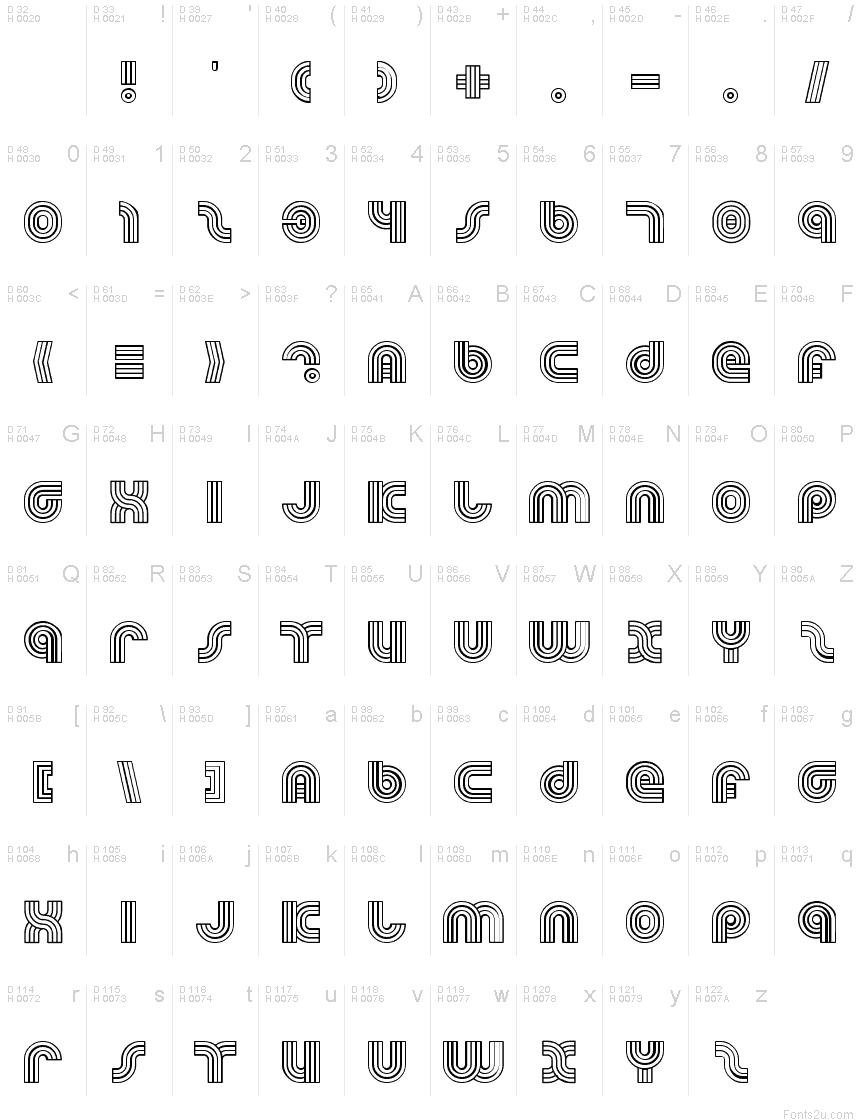
Dreamland von dustBUST Fonts ist eine kostenlose, flippige Display-Schrift, die an handgezeichnete Neonröhren erinnert. Jeder Buchstabe setzt sich aus konzentrischen Streifen zusammen, die sich zu hohen, geschwungenen Formen aufbauen – ein fast hypnotischer, labyrinthartiger Rhythmus. Da die Linien klar und gleichmäßig angeordnet sind, wirkt das Schriftbild trotz der lebendigen Dynamik kontrolliert und gut lesbar.
Setzen Sie Dreamland in großen, fetten Graden ein, damit die geschichteten Bögen auf Musikplakaten, Festival-Branding, Retro-Verpackungen, ausgefallenen Logos, Headlines und Social-Media-Grafiken ihre volle Wirkung entfalten. Diese kostenlose Schrift glänzt vor allem, wenn sie Platz zum Atmen hat. Halten Sie daher Ihre Texte kurz und kombinieren Sie sie für ergänzende Inhalte mit einer klaren, geometrischen serifenlosen Schrift.